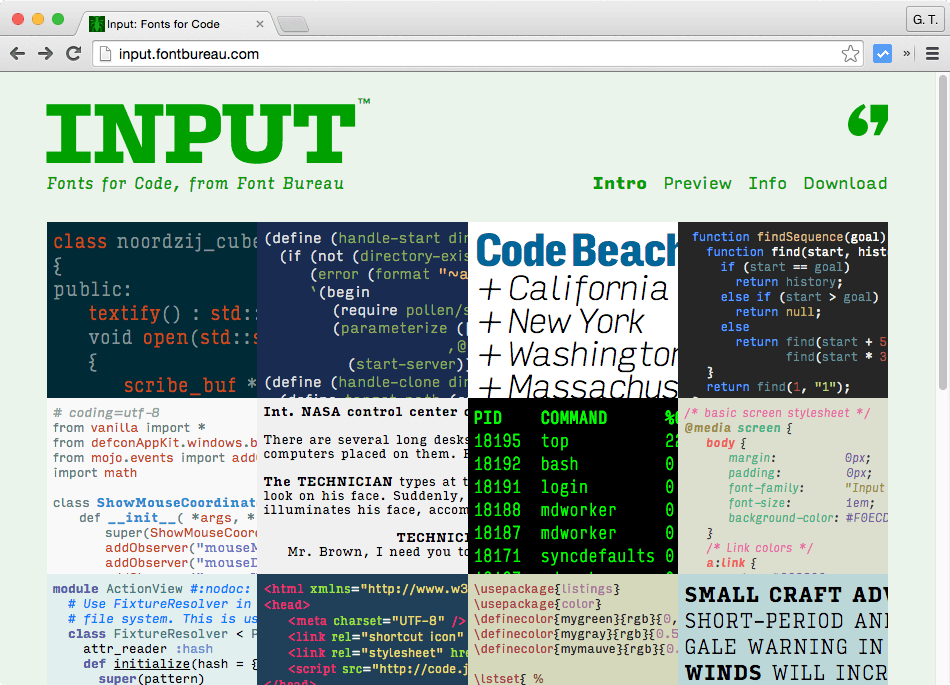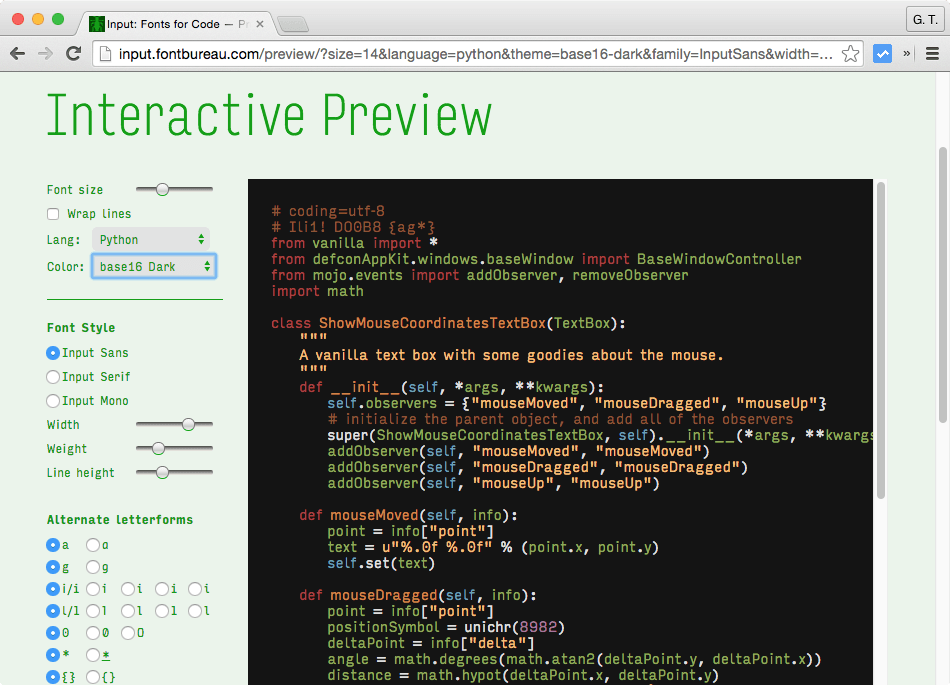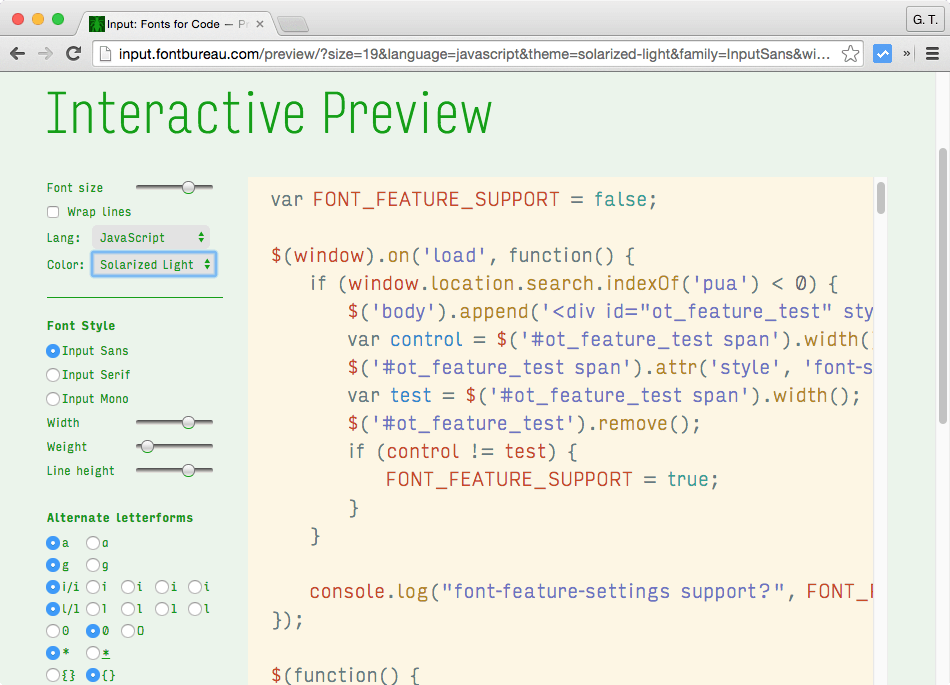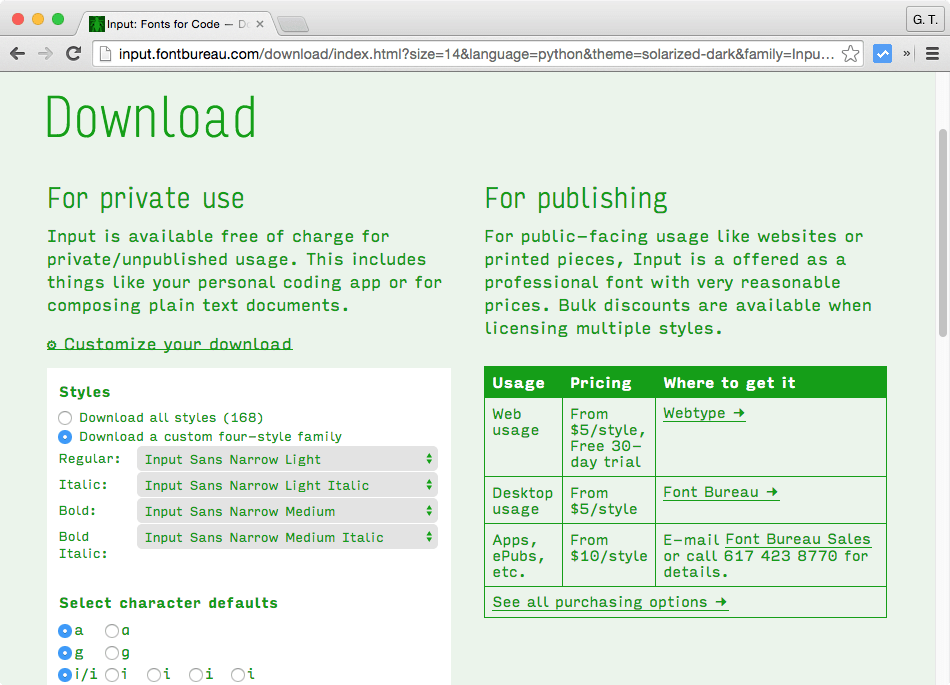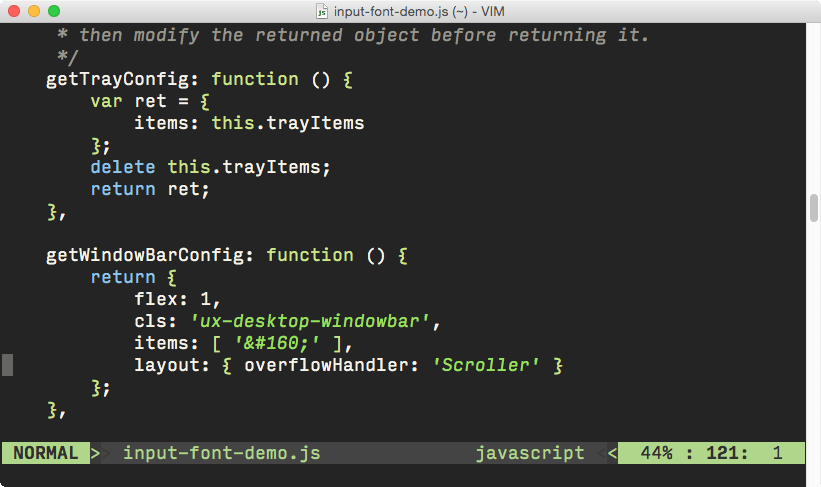
Input 是一套專門用於顯示程式碼的字型集,包含各種漂亮的等寬字型,對於程式設計師非常有用。
許多的工程師、程式設計師甚至是理工科的研究生,時常需要撰寫大量的程式或是閱讀程式碼,若有一個漂亮的字型能讓程式碼賞心悅目,不管是在工作效率或是心情上,都會有幫助。
我們之前也介紹過許多適合程式設計師使用的字型,而這裡再介紹一個由 David Jonathan Ross 所製作的字型集,由於這些字型是特別為了顯示程式碼而設計的,除了等寬的特性之外,還加強了文字線條的清晰度、字母寬度的選擇性,甚至可以從字型的的選擇調整行高,讓程式碼可以非常漂亮的顯示在螢幕上。
這是 Input 字型的官方網站,首頁展示了各種漂亮的字型。
網站上有提供一個互動式預覽功能(Interactive Preview),我們可以透過這個小工具調整字型的設定,看看各種組合所產生的效果。
這裡也內建一些不同的佈景主題,我們可以根據亮色系與暗色系選擇不同的字體來搭配。